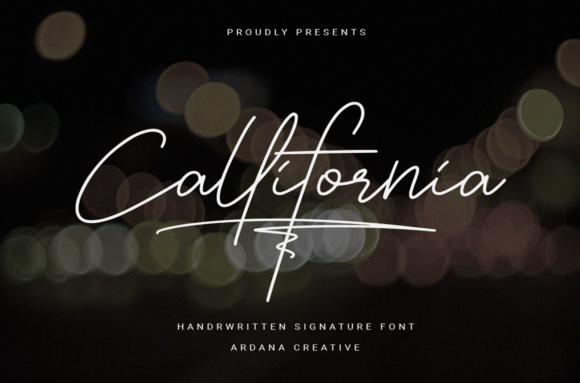
Callifornia
การค้นหาองค์ประกอบการออกแบบที่เหมาะสมอาจเป็นเรื่องท้าทาย แต่ Callifornia นำเสนอคอลเลกชันที่โดดเด่นซึ่งช่วยยกระดับงานของคุณได้ทันที
สร้างขึ้นอย่างแม่นยำ Callifornia ให้เวกเตอร์ที่สะอาด พิมพ์ตัวอักษรที่ราบรื่น และใบอนุญาตเชิงพาณิชย์เพื่อความสบายใจ
ไม่ว่าคุณจะสร้างผลิตภัณฑ์ POD (Print on Demand) คำเชิญงานแต่งงาน หรือกราฟิกโซเชียลมีเดีย Callifornia ก็เหมาะสมอย่างยิ่ง